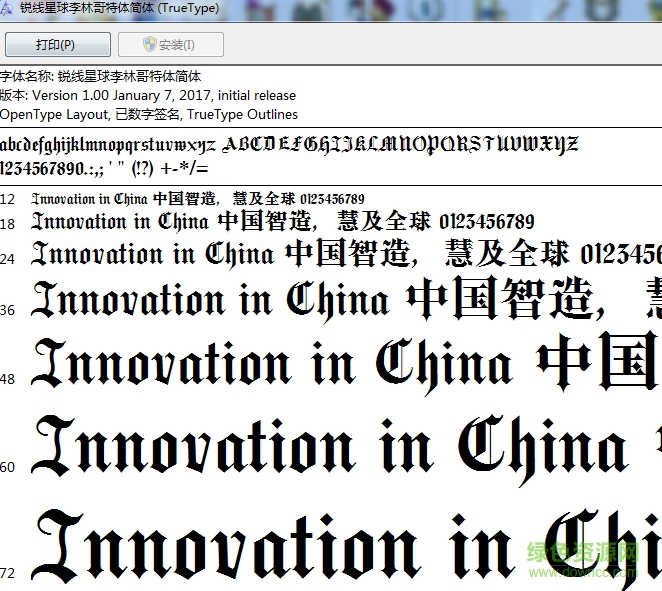
銳線星球李林哥特體簡體是一款超好用的個性字體,該字體可以廣泛應(yīng)用于廣告設(shè)計、宣傳海報、ppt、影視制作以及任何使用文字的領(lǐng)域,有需要的朋友可以免費(fèi)下載收藏。
銳線星球李林哥特體簡體是一款極具個性的字體,該字體的形體非常飄逸,給人大氣的感覺。適用于美工設(shè)計,有需要的用戶可以來綠色資源網(wǎng)下載使用!